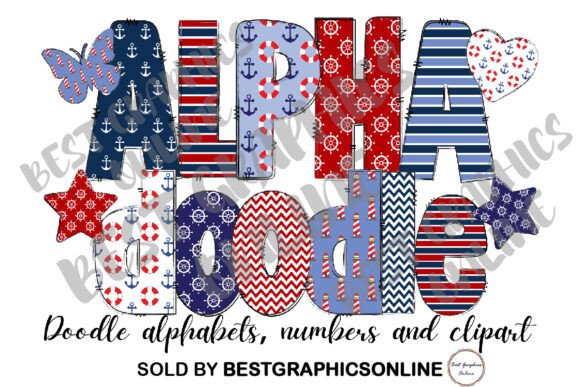
Nautical Sailing Doodle Alphabet Letters
Nautical Sailing Doodle Alphabet Letters์™€ ๊ฐ™์€ ๊ณ ํ’ˆ์งˆ ์ž์‚ฐ์„ ์ฐพ๊ณ  ์žˆ๋‹ค๋ฉด ์ด ํ”„๋ฆฌ๋ฏธ์—„ ํŒจํ‚ค์ง€๋Š” ์ฐฝ์˜์ ์ธ ํ”„๋กœ์ ํŠธ๋ฅผ ์œ„ํ•œ ํ™˜์ƒ์ ์ธ ์„ ํƒ์ž…๋‹ˆ๋‹ค.
์ •๋ฐ€ํ•˜๊ฒŒ ์ œ์ž‘๋œ Nautical Sailing Doodle Alphabet Letters๋Š” ๊น”๋”ํ•œ ๋ฒกํ„ฐ, ๋ถ€๋“œ๋Ÿฌ์šด ํƒ€์ดํฌ๊ทธ๋ž˜ํ”ผ ๋ฐ ์•ˆ์‹ฌํ•  ์ˆ˜ ์žˆ๋Š” ์ƒ์—…์šฉ ๋ผ์ด์„ ์Šค๋ฅผ ์ œ๊ณตํ•ฉ๋‹ˆ๋‹ค.
POD(์ฃผ๋ฌธํ˜• ์ธ์‡„) ์ œํ’ˆ, ๊ฒฐํ˜ผ์‹ ์ดˆ๋Œ€์žฅ ๋˜๋Š” ์†Œ์…œ ๋ฏธ๋””์–ด ๊ทธ๋ž˜ํ”ฝ์„ ๋งŒ๋“ค ๋•Œ Nautical Sailing Doodle Alphabet Letters๋Š” ์ด์ƒ์ ์ธ ์„ ํƒ์ž…๋‹ˆ๋‹ค.